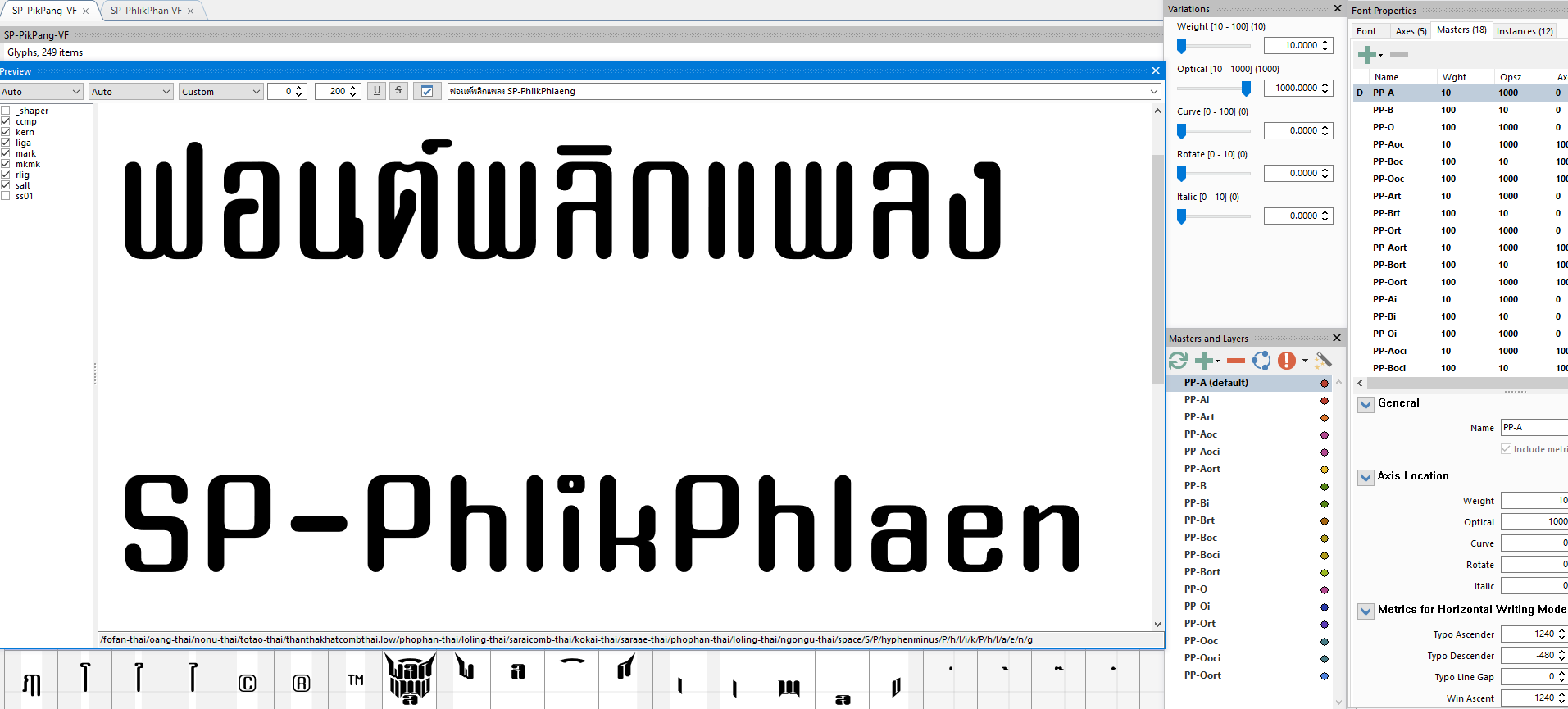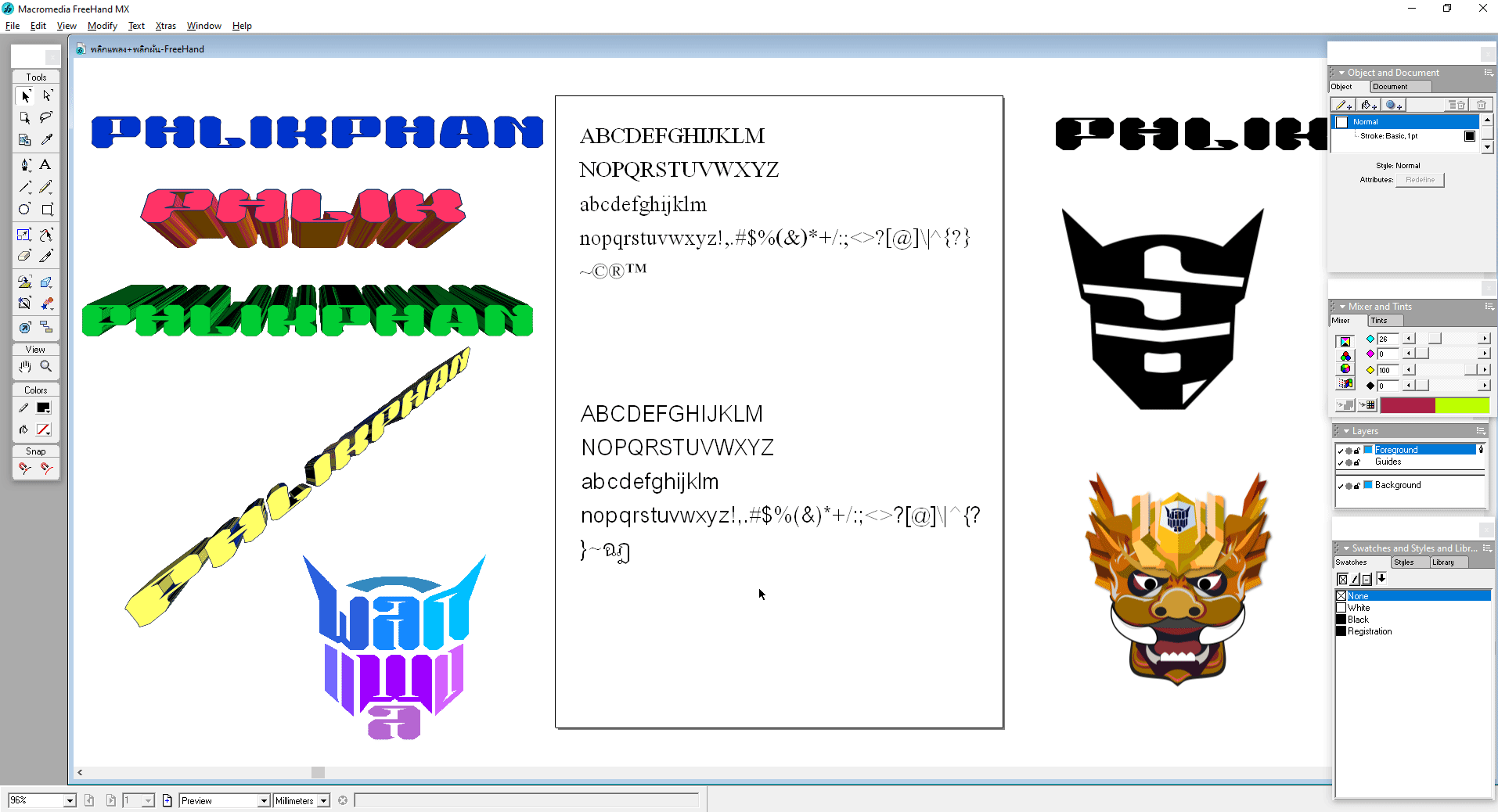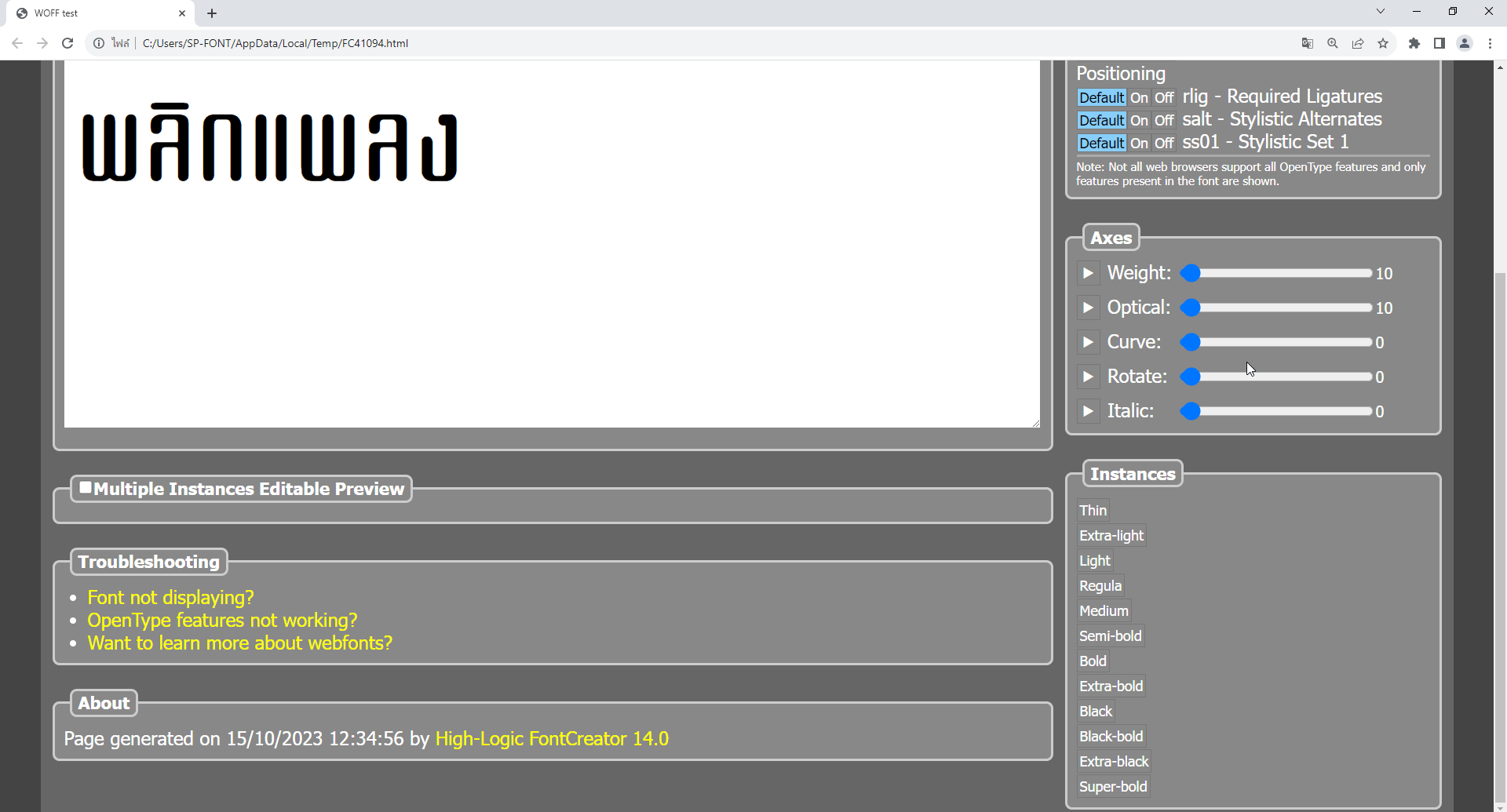
(◣_◢)พลิกแพลงแปลงฟอนต์(◣_◢)
กำเนิดจักรกลอักษร
ก่อนจะเข้าเรื่อง "ทรานสฟอนต์เตอร์" ต่อ ขอนำเรื่อง ภาษาบาลี มาแทรกไว้ ซึ่งได้เคยนำเสนอไปแล้ว แต่รู้สึกว่ายังไม่ละเอียดพอ
ตะก่อนมัวแต่งุ่นง่านเรื่องการออกแบบ-ฟีเจอร์ ต่างๆ ไปจนลืมเรื่องการใช้งานฟอนต์ด้านภาษาบาลี
ถึงฟอนต์เรา จะไม่เหมาะ หรือไม่นิยมไปใช้งานด้านนี้ แต่ในฐานะผู้สร้างสรรค์ ควรคำนึงถึงด้วยก็ดี
เพื่อเพิ่มความหลากหลายในการใช้งานให้กับฟอนต์ แถมปลูกฝังให้ทำติดเป็นนิสัย (ขี้ลืม)
เพราะผม ก็เพิ่งจะมาให้ความสำคัญ ตอนนี้เหมือนกันนี่แหละ 555
อิมสฺมิํปาปุณิํสุฐาตุํญาติํทิฏฺฐุปญฺญินฺทฺริยํรตฺตญฺญูอัญญาโกณฺฑญฺญเสยฺโย
บาลี (บาลี: ปาลิ पालि; สันสกฤต: पाळि ปาฬิ; อังกฤษ: Pali) แปลว่า "ภาษาที่รักษาไว้ซึ่งพระพุทธวจนะ"
(แปลตาม พระอรรถกถาจารย์ ที่ท่านได้ให้ความหมายเอาไว้ ในหลักสูตรเปรียญธรรมดั้งเดิม ไม่ได้ฝักใฝ่ ตามลัทธิ ตัวตนบุคคลอาจารย์ท่านใด)
ภาษาบาลี จะมีลักษณะดังที่เห็น पालि มีไวยากรณ์เหมือนกันกับภาษาสันสกฤตในอักษรเทวนาครี มีการแปลออกมาเป็นภาษาต่างๆทั่วโลก
ที่เราเห็นเป็นภาษาไทย อันนั้นท่านแปลออกมา โดยใส่ตัวอักษรไทยลงไปแทนการออกเสียงสำเนียงคำพูดเท่านั้นนั่นเอง
ตั้งค่า MS-Word พิมพ์ภาษาบาลี นิคหิต+พินทุ
เพื่อการใช้งานถูกต้องตามหลักภาษาบาลีไวยากรณ์ มีจุดสำคัญที่ต้องเช็คตามนี้
1.จุดล่าง เรียกว่า พินทุ เป็นเครื่องหมายบ่งบอกว่า
-หากหน้าพินทุมีสระอยู่ เป็นตัวสะกด จะไม่ออกเสียงตัวมีพินทุ เช่น มนุสฺโส (มะ+นุด+โส=มนุษย์)
-หากหน้าพินทุไม่มีสระกำกับ ออกเสียงเหมือนมีไม้หันอากาศอยู่ด้วย เช่น จกฺขุ (จัก+ขุ=นัยน์ตา)
-หากมีพินทุ อยู่หน้า จะเป็นตัวควบกล้ำ เช่น พฺรหฺม อ่านว่า พรำ+มะ ออกเสียงรวบกันคนละครึ่ง
ถ้าออกเสียงเป็น พรม+มะ นั่นเป็นคำไทย ไม่ใช่ภาษาบาลี
-ออกเสียงรวบคนละครึ่ง เช่น กตฺวา=กัด+ตัว สุตฺวา=สุด+ตัว
2.จุดบน เรียกว่า นิคหิต หรือ นฤคหิต
-ออกเสียงเหมือนมี  อัง อยู่ด้วย เช่น อกฺขรํ (อัก+ขะ+รัง=ซึ่งอักษร-คำว่าซึ่งมาจากวิภัตติไวยากรณ์)
-มีสระอุ ร่วมอยู่ด้วย ออกเสียงเป็น อุง เช่น สตฺตกฺขตฺตุํ (สัด+ตัก+ขัด+ตุง=สิ้น 7 ครั้ง)
-มีสระ อิ ร่วมอยู่ด้วย ออกเสียงเป็น  อิง เช่น อิมสฺมิ (อิ+มัด+สะ+หมิง=ในนี้)
3.ฐ+ญ ไม่มีฐาน เมื่อเวลาพิมพ์เป็นภาษาบาลี จะต้องไม่มีฐานเชิง ไม่ว่าจะมีสระพินทุอยู่ด้วย หรือไม่มีก็ตาม
เพื่อกำหนดได้หมายรู้ว่าเป็นภาษาบาลี และรักษาการเขียนแบบโบราณดั้งเดิมให้ถูกต้องตามหลักบาลีไวยากรณ์
ซึ่งในเทมเพลต มีอยู่แล้ว แต่เป็นการหลบเมื่อเจอสระเท่านั้น ผู้ออกแบบ จะต้องกำหนดเพิ่มเอง
ว่าเมื่อเวลา ญ กับ ฐ อยู่เดี่ยวๆ ไม่มีสระ พินทุอยู่ด้วย ก็สามารถ ใช้แบบไม่มีเชิงก็ได้ ที่เราเห็นในหนังสือสวดมนต์
ตำราคัมภีร์ต่างๆ คนทำเขาก็ต้องการใช้แบบที่ว่า แต่ในฟอนต์ ไม่มีให้เลือกใช้นั่นเอง
ส่วน พยัญชนะที่ไม่มีสระกำกับ ออกเสียงเหมือนมีสระ อะ อยู่ด้วย เพียงแต่ไม่เห็นรูป เช่น วจน (วะ+จะ+นะ=คำพูด หรือวาจา)
สำเนียงภาษาภาคใต้ ที่มีฮิต่อท้าย หรืออีสาน ที่มี ติ ต่อท้าย เช่น  อีหลีติ ผู้เขียนคิดว่า น่าจะได้รับอิทธิพลมาจากภาษาบาลี
ยกตัวอย่าง เช่นคำว่า วิญญูหีติ (บทสวดสรรเสริญพระธรรมคุณ) มาจากรากศัพท์ วิ+ญา+หิ+อิติ
-วิ แปลว่า วิเศษ/แจ้ง/ต่าง เป็นศัพท์พิเศษ
-ญา แปลว่า ผู้รู้ มาจาก ญา ธาตุ
-หิ เป็น ตติยาวิภัตติ แปลว่า ด้วย/โดย/อัน/ตาม/เพราะ/มี
-อิติ แปลว่า ดังนี้ ใช้เป็นคำต่อท้ายประโยค
ฉะนั้น คำว่า "วิญญูหีติ" มาจาก ญา ธาตุ ในความเป็นผู้รู้ แปลง สระอา เป็น อุ เติม วิ ศัพท์พิเศษข้างหน้า ซ้อน หรือ สังโยค ญ
ลง หิ ตติยาวิภัตติ  ฑีฆะ อุ เป็น อู สนธิกับ อิติ เป็น หีติ ให้อ่านออกเป็นเสียงสูง ตามสำเนียงคำพูดของภาษามคธ (บาลี)
อ่านว่า "ฮีติ" เพราะพยัญชนะในภาษาบาลี ไม่มี ฮ.นกฮูก ครั้นจะมาใช้ ฮ. มันไม่ใช่พยัญชนะในบาลี จึงใช้ ห.หีบแทน
สำหรับ อิติ แปลว่า "ว่า" ท่านนิยม ใช้เป็นประโยคคำพูด หรือบอกเล่า เช่น ดังได้ยินมาว่า"................................"ดังนี้
มักจะมีคำว่า "อิติ" ต่อท้ายเสมอ ชาวบ้านจึงนิยมใช้คำว่า ฮิ หรือ ติ เป็นคำลงท้าย เหมือนดังเช่นในภาษาบาลีนั้นนั่นเอง
-สระ ไอ สระ ใอ ไม่มีใน ภาษาบาลี ท่านใช้ เ-ย แทนสำเนียงการพูด เช่น อาหุเนยฺโย ปาหุเนยฺโย ทกฺขิเณยฺโย
อ่านว่า อา+หุ+ไนย+โย /ปา+หุ+ไนย+โย / ทัก+ขิ+ไนย+โย ไม่ออกเสียงเป็น เนย+โย
ตรงนี้ จะเป็นเรื่องราวประกอบในการชี้เป้าให้กับผู้ออกแบบสร้างสรรค์ฟอนต์ ว่าจะใช้วิธีไหน ให้ฟอนต์ตนเองมีออฟชั่นเสริมอย่างที่ว่า
***หมายเหตุ ที่เราใช้ เราเห็นอยู่ปัจจุบันนี้ ไม่ได้ผิดอะไร แต่ที่นี้ เป็นการเพิ่มรายละเอียดให้ล้ำลึกยิ่งขึ้นสำหรับผู้สนใจนั่นเอง
แบบล่างสุดท้าย ถึงจะถูกต้องตามอักขระวิธี
พอ จะ นะ
#4
ทีแรก..คิดว่า..จะทำ VariableFont แค่ชุดเดียวพอ ที่เคยนำเสนอไปก่อนหน้านั้น..แต่รู้สึกว่า..ยังไปไม่สุด...เหมือนมัน
ยังขาดอะไรอยู่ที่ยังไม่ได้ทำ....(ว่าซั้น) เพราะการสรรค์สร้าง  ไม่มีขอบเขตจำกัด  กว้างใหญ่ไพศาล  ดังเช่นพหุจักรภพ
มันคือปริซึมจินตนาการเป็นไปได้ไม่สิ้นสุด ตั้งแต่ระดับเล็กน้อยจนถึงเกิดปรากฏการณ์ผีเสื้อกระพือปีก (Butterfly Effect)
เป็นวิถีทางที่แปรเปลี่ยนไปอย่างสิ้นเชิง..จนมันไม่ใช่ตัวอักษรในแบบที่โลกเรารู้จักอีกต่อไป (จนถึงไม่จักเลย..มั้ง..ง)
.....จวบจนเวลามาถึงโปรเจคน้อยๆ ชุดนี้ เป็นอีกหนึ่งในแฟรนไชส์ของมัลติเวิร์ด จักรวาลฟอนต์ ที่ได้ถือกำเนิดก่อเกิดขึ้น
เพื่อมาเขย่าวงการจักรวาลฟอนต์ ให้สั่นสะเทือนเลื่อนลั่น เอาแค่ 0.1 ริคเตอร์พอ...เพราะหลีกทางให้กับฟอนต์ลายมือ
ที่ถาโถมกระหน่ำมาอย่างไม่ขาดสาย เกินกว่า 9 ริคเตอร์ แถมท้ายอาฟเตอร์ช็อก..ก..ก.ต่อเนื่องกันมาอย่างยาวนาน
Level Scroll Bar
มาถึง.....การฝึกทดสอบลงภาคพื้นสนามจริง ของเหล่าบรรดาทีม คอบร้าโกลด์
Photoshop
Illustrator
MS Word ไม่รองรับ Variable แต่จะมองเห็นเป็นฟอนต์ที่แยกเป็นน้ำหนักออกมา (เช่นเดียวกับโปรอื่นๆที่ไม่รองรับ..แต่ยังใช้ได้ในรูปแบบนี้)
Web  Browser รองรับรูปแบบสี
High-Logic FontCreator
โปรที่ไม่รองรับ VariableFont หรือเป็นโปรรุ่นพี่เก๋ากึ๊ก จะไม่มีออฟชั่นสไลเดอร์ปรับเลื่อน เช่น
เมื่อตอนที่วินโดวส์ 7 เป็นเจนล่าสุดในยุคนั้น